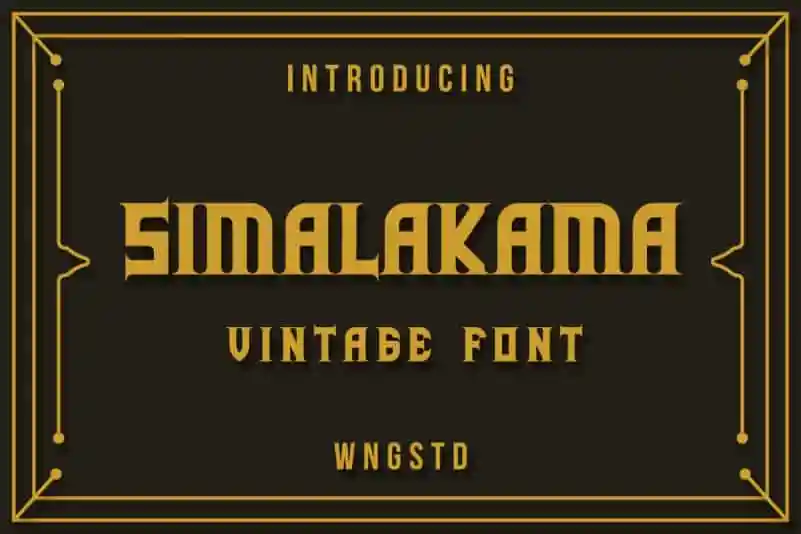
Simalakama Vintage Display Font – Download Grátis
A Simalakama Vintage Font é uma seleção de tipo em letra gótica vintage com traços sólidos e autênticos. Esta escolha para sua próxima peça de design certamente irá destacar-se, oferecendo um toque nostálgico que combina bem em diversos projetos. Este font é perfeito para qualquer ideia de design, seja ela uma capa de livro, um cartão personalizado ou até mesmo o logotipo da sua marca. Com a Simalakama Vintage Font, você terá a oportunidade de trazer um toque especial e único ao seu trabalho de design, garantindo que ele se destaque da multidão. Com certeza vale a pena explorar mais sobre esta font para enriquecer seus projetos gráficos!